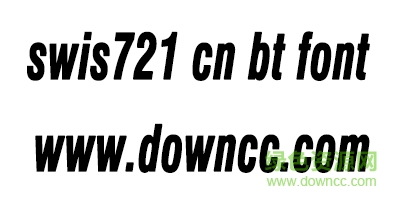
swis721 cn bt是一款非常有特色的英文字體,這款字體字形傾斜,字體筆畫(huà)粗壯,整體效果非常出色,喜歡這款字體的朋友歡迎來(lái)綠色資源網(wǎng)免費(fèi)下載使用。
swis721 cn bt字體是一款英文字體,這款字體具有非常強(qiáng)的個(gè)性風(fēng)格,適合各類(lèi)設(shè)計(jì)領(lǐng)域使用,有需要的朋友就趕快來(lái)綠色資源網(wǎng)下載吧!